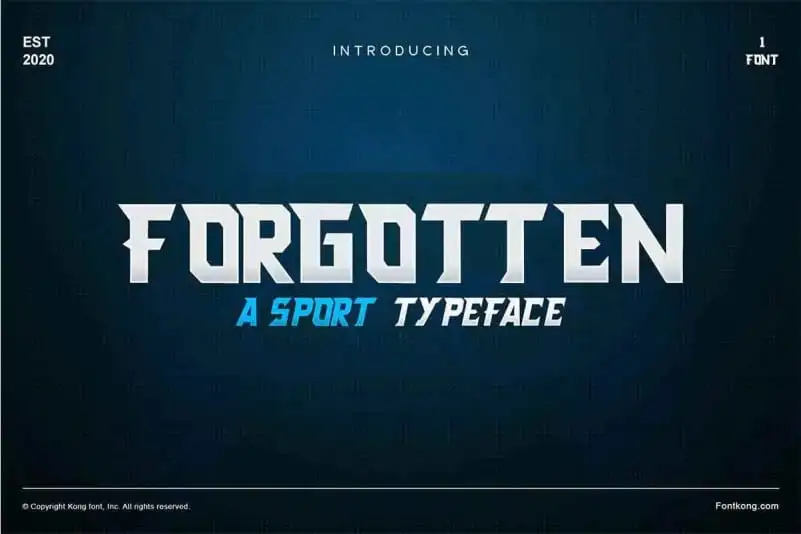
Forgotten Display Font – Download Grátis
A Forgotten Display Font é uma fonte de exibição que traz uma forte identidade visual, com formas geométricas retangular e linhas modernas, sem perder seu charme contemporâneo. Esta fonte apresenta tanto letras maiúsculas quanto minúsculas, incluindo ascentes e ligaduras adicionais para um acabamento mais elaborado. Além disso, também oferece alternativas estilísticas que permitem uma grande variação de estilo ao usar a mesma fonte. As características numerosas e algarismos especiais proporcionam flexibilidade em diversos contextos, enquanto símbolos monetários e outros simbolos adicionais aprimoram seu uso para ambientes específicos. Em resumo, esta fonte é perfeita tanto para gráficos de marca quanto para materiais publicitários que exigem uma exibição visual inovadora e vibrante.